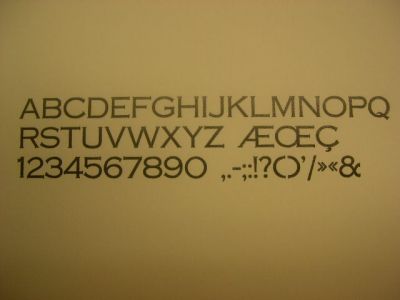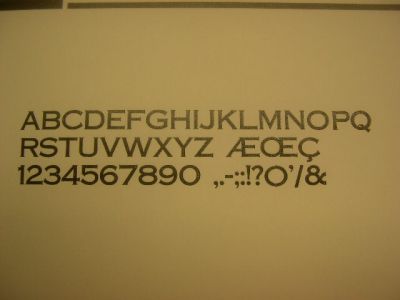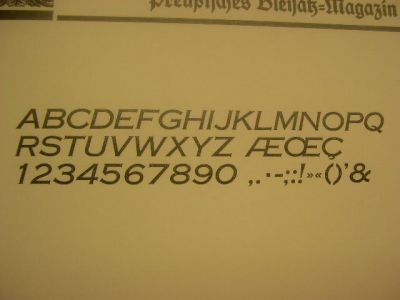
Mimosa von C.E.Weber in einer DDR-Version?
ich habe ein Problem:
Einen ganzen Kasten voll mit drei Schnitten mit nagelneuer Schrift.
Der Kasten ist sauber beschriftet und man sollte meinen: feine Sache.
Problem - dort steht:
20 p Mimosa
20 p Mimosa halbfett
24 p Mimosa kursiv
Und? Genau. Es gibt die Mimosa aus dem Jahr 1928 der Schriftgießerei C.E.Weber nicht in kursiv.
Es kann eigentlich nur sein, daß das gar nicht die Mimosa ist.
Aber ich kenne keine ähnliche Schrift. Die Mimosa ist ja nun
wirklich nicht besonders schwer zu identifizieren.
Ich habe mir dann mal die Copperplate Gothic von Linotype angeschaut:
Sicher, vom Stil her paßt es schon. Aber die Serifen sind ausgeprägter bei der amerikanischen Schrift.
Und selbst, wenn nicht: Diese Schrift wird wohl kaum in der zweiten Hälfte
der 20er Jahre als Bleisatz-Schrift nach Deutschland gekommen sein.
Das glaube ich einfach nicht.
Eine Idee habe ich: Kann es sein, daß TypoArt Dresden eine Art
Konkurrenz-Schrift zur Mimosa von C.E.Weber hergestellt hat?
Ein Indiz: In demselben Schrank waren auch noch andere DDR-Schriften:
Fundamental und Super-Grotesk.
Hat jemand vielleicht eine Idee?
Kennt jemand aus der Leipziger Typographen-Gruppe die Schriftbestände der TypoArt vielleicht etwas besser als ich und kann helfen?
also ich weiss, das wir eine mimosa zu ddr zeiten
als bleisatzschrift hatten, wo die herkam kann ich
dir allerdings nicht beantworten – aber ich schau
mal in meinen typoartmuster nach.
Mh.. das ist interessant.
Aber korrigier mich, wenn ich falsch liege:
DDR-Setzereien haben wohl nicht bei Schriftgießereien in West-Deutschland einkaufen können, oder? Vielleicht habt Ihr Vorkriegsbestände gehabt?
Typoart hat einige Schriften von Schriftguss Dresden übernommen, da Schriftguss ein Betriebsteil von Typoart war.
Mimosa
Mimosa Halbfett
Mimosa Kursiv bzw. Halbfett Kursiv (identisch)
genauso wie
Marko
Minister ...
Thannhaeuser ...
Super ...
Schriftguss hatte auch amerikanische Designs im Angebot wie die Cooper und die Ohio.
daß die Schriften der Schriftguß A.-G. von der TypoArt übernommen wurden, ist mir natürlich bekannt.
Aber die Mimosa war doch gar keine Schriftguß-Schrift, sondern stammte von C.E.Weber in Stuttgart. Und in deren Schriftmustern wird eine Kursiv-Garnitur überhaupt nicht erwähnt, nur die normale und die halbfette Garnitur. Beides mit Erstguß-Jahr 1928 und sie werden als Hausschnitt angegeben.
Andererseits hat die Schriftguß A.-G. den Vertrieb der National von Ludwig & Mayer mit übernommen. Mit eigenen Schriftmuster unter eigenem Label und ohne Nennung von L&M (aber sicher mit deren Einverständnis, das Markenrecht war ja eindeutig).
Aber dann verstehe ich nicht, warum C.E.Weber die Kursiv-Version nicht nennt. Findet man über die TypoArt-Mimosa irgendwo etwas offiziell Schriftliches? Eine Skizzenkartei o.ä.?
Auf den Karteikarten von Typoart ist als Erstguß 1920 angegeben mit dem Vermerkt "Hausschnitt". Kartennummern TD5.2a, TD5.2c, TD5.2k
Schriftguss und C.E.Weber hatten sowas wie eine Partnerschaft. Ähnlich wie Klingspor and D.Stempel.
Sehr interessant.
Auf meinen Typokarteien der C.E.Weber steht als Erstguß-Jahr 1928.
Und, wie gesagt, dort ist in der Zusammenfassung aller vorhandenen Garnituren die Kursiv-Variante gar nicht vorhanden.
Diese ganze TypoArt muß schon ein rechtes Phänomen gewesen sein.
Und Schriftguß hatte wohl die modernste Art des Vertriebs für die damalige Zeit, oder? OEM-Produkte für andere Gießereien unter dem Original-Namen aber eigenem Label verkaufen - schon toll.
Schriftguss bitte immer mit ss schreiben, ist ein Eigenname. :-)
Ja, Schriftguss war recht modern und wenn ich mir die Muster ansehe, auf gestichenem Papier mit neonfarben gedruckt, die heute noch so frisch daherkommen, erinnert mich das nicht an die 30er Jahre. Die Musterbücher von Schriftguss aus den 1930 Jahren sehen eher so aus wie die Bücher von Berthold aus den 1960er Jahren, also schon sehr aufgeräumt und schlicht.
Das Bild stammt von einem Werbe-Schriftmuster der National von 1934. Mit Empfehlung an den Pg. Franz Engelmeier, den damaligen Ortsgruppenleiter der NSDAP. Naja.
Sehr gut gefallen mir die Schaefer-Versalien dieser Schriftgießerei.
Das ist schon beachtlich, was man als Setzer gestalterisch damit machen konnte.